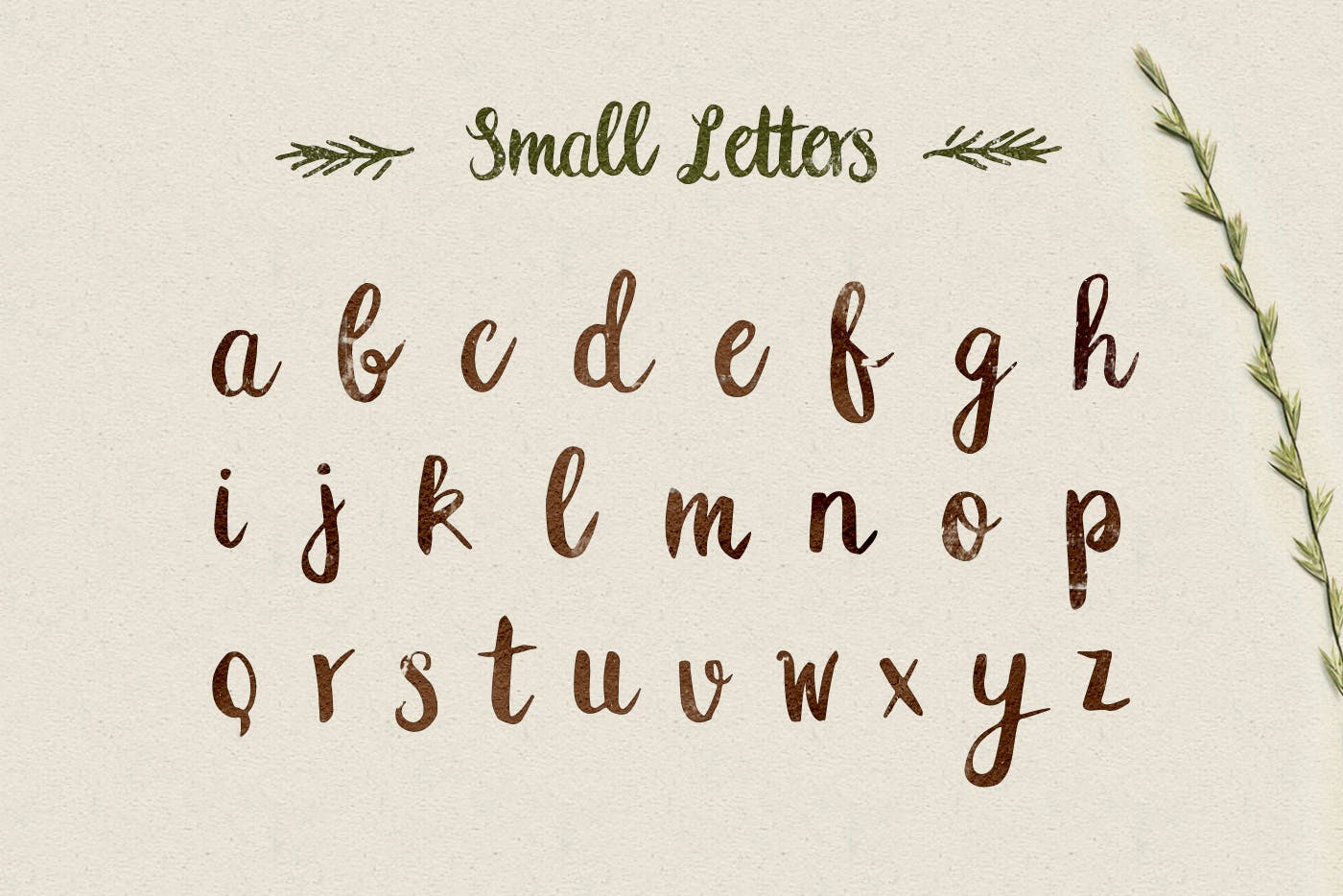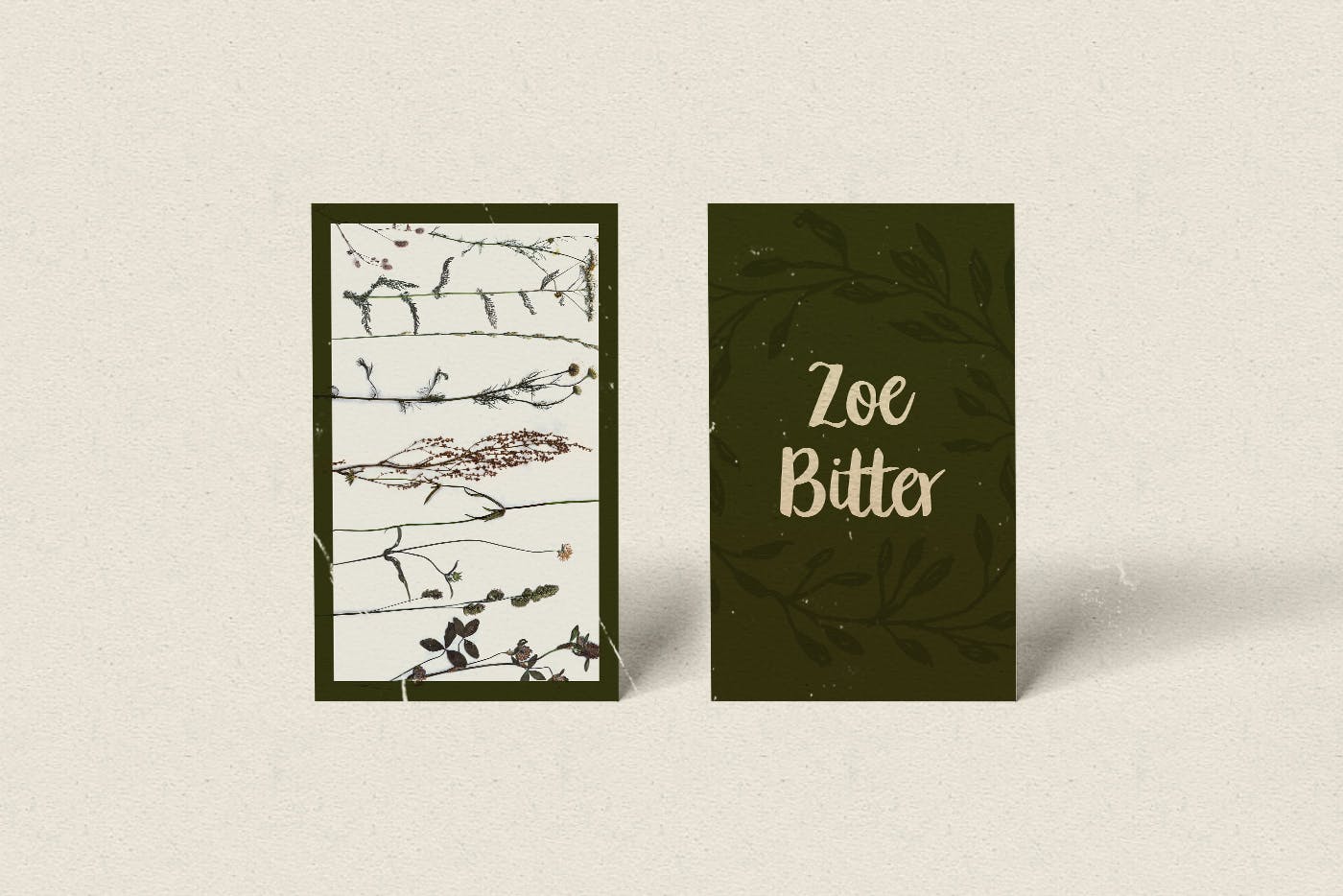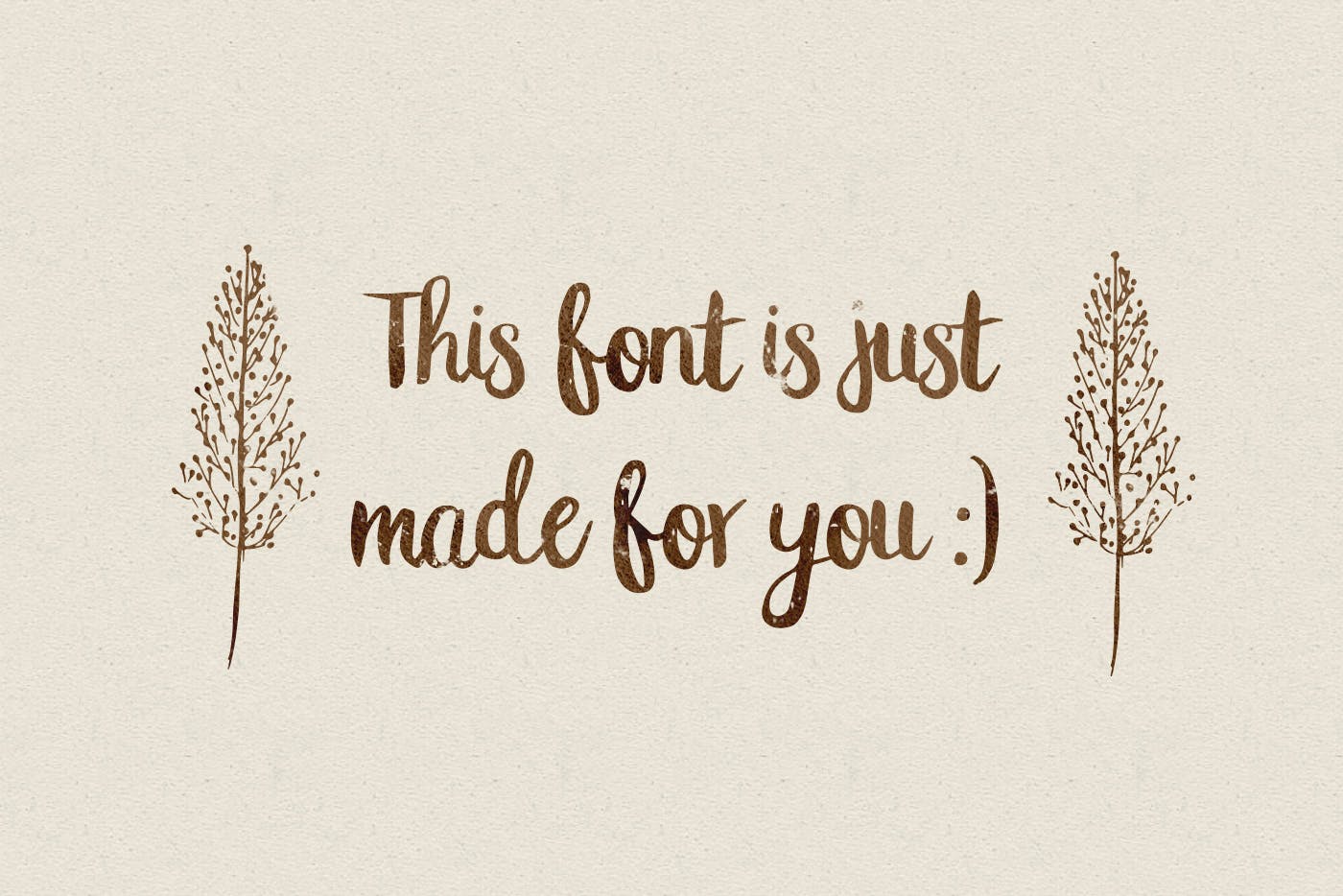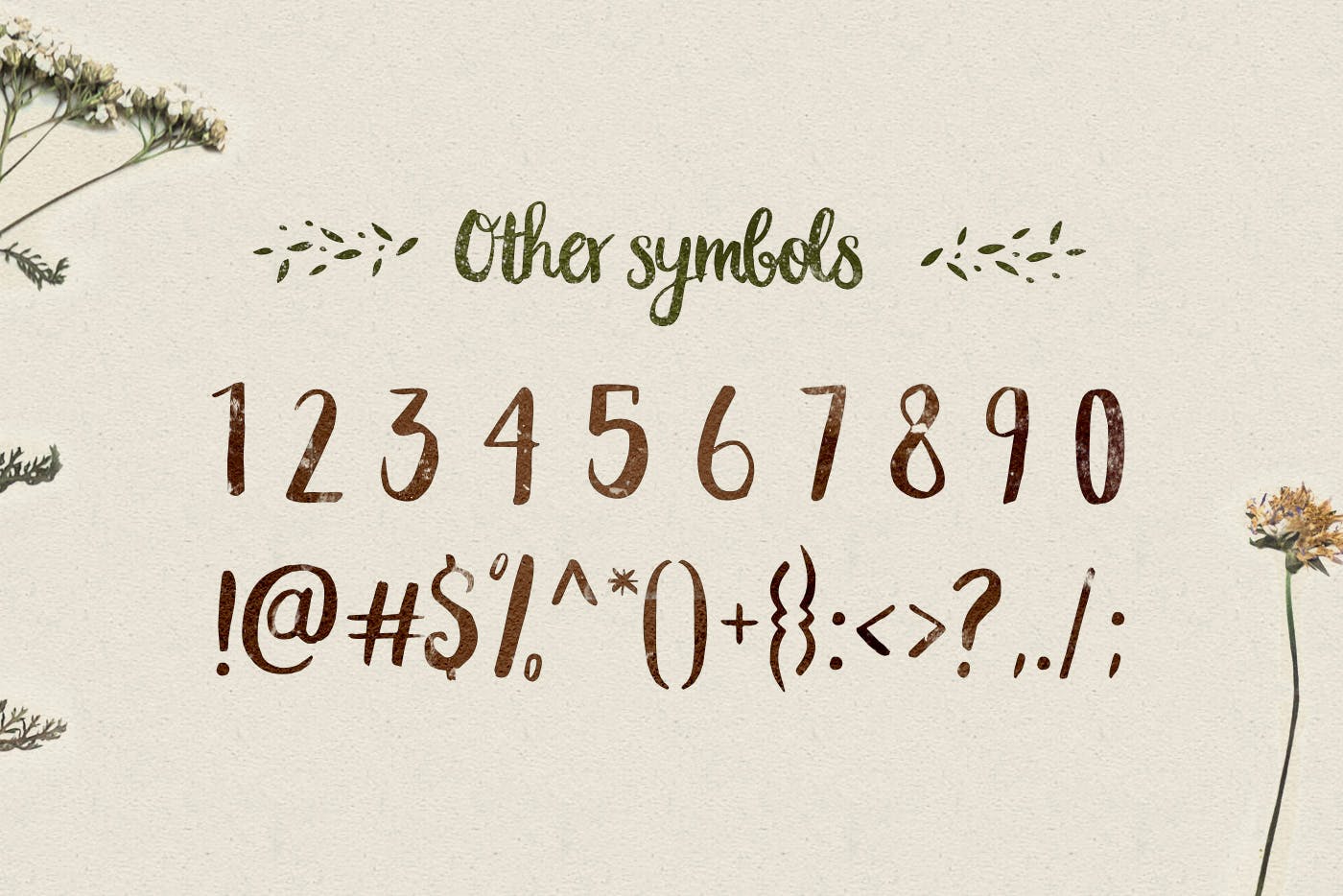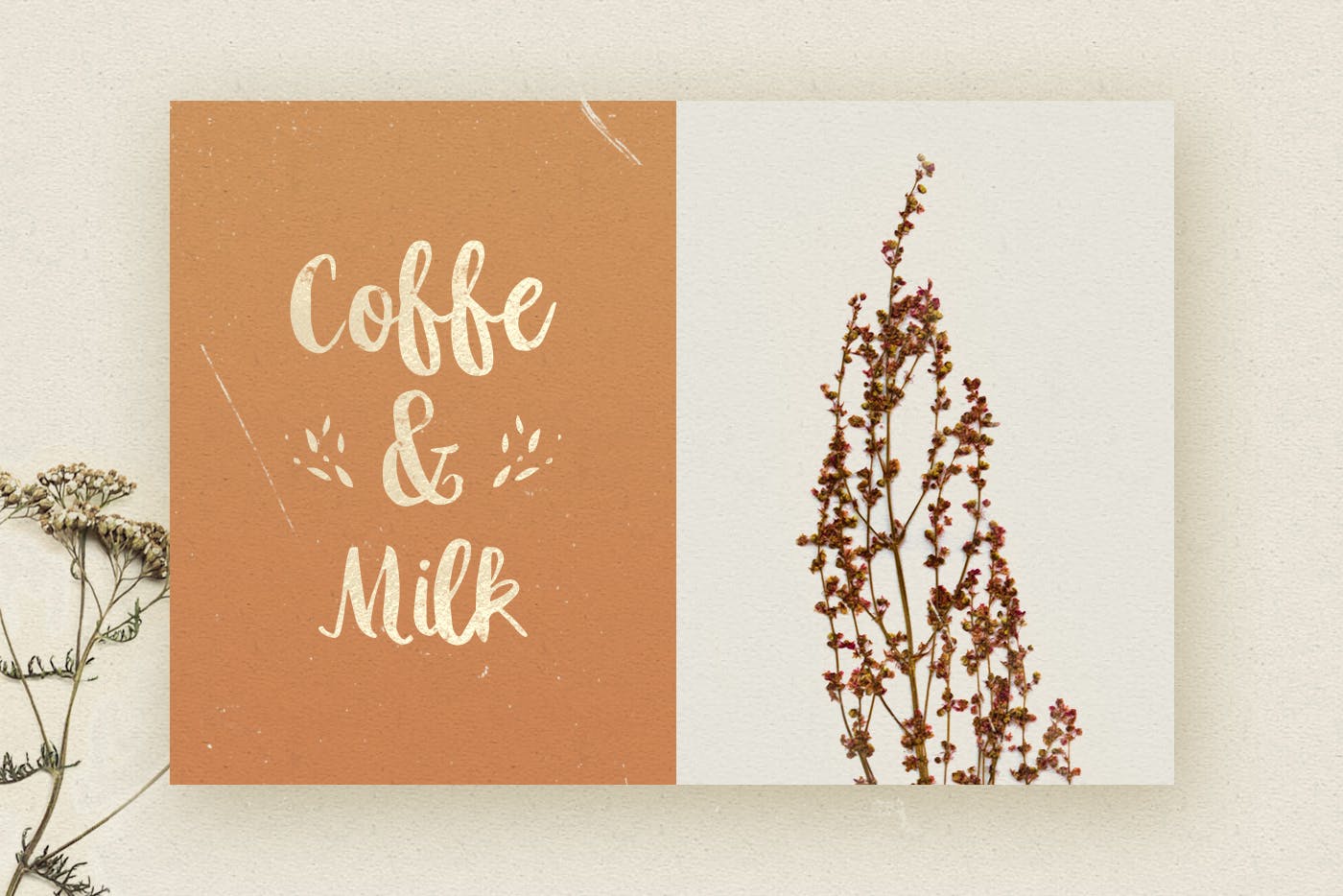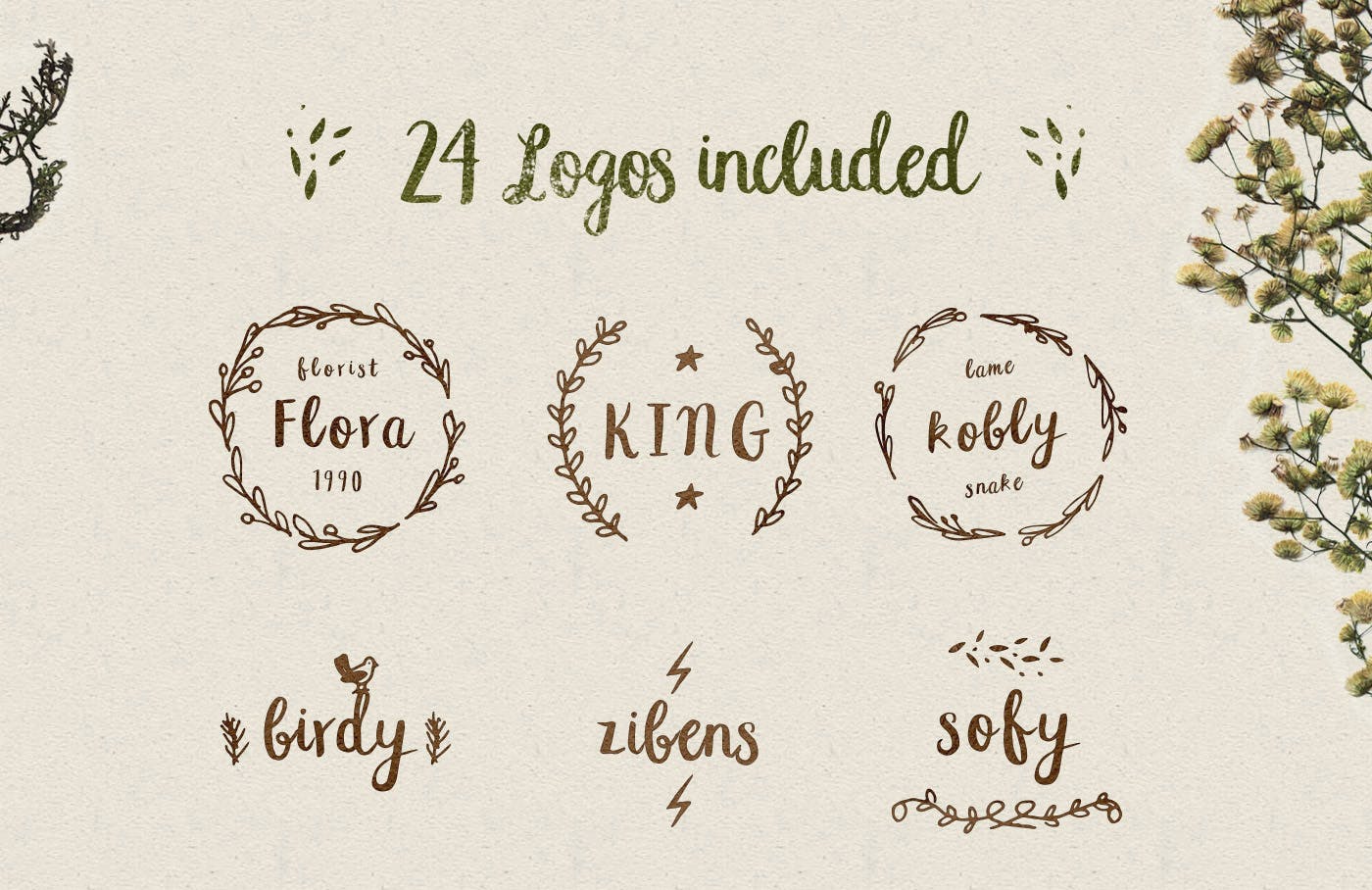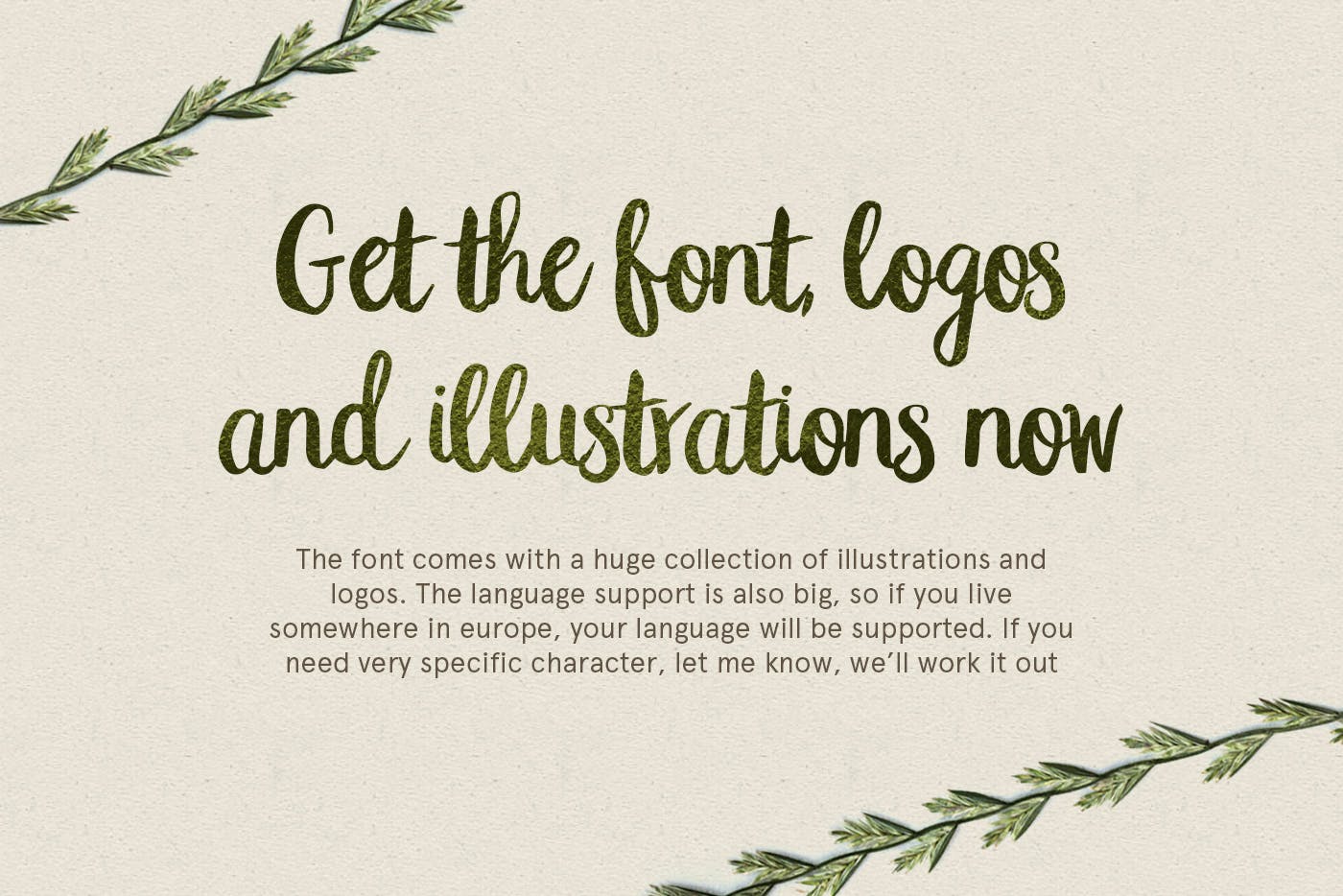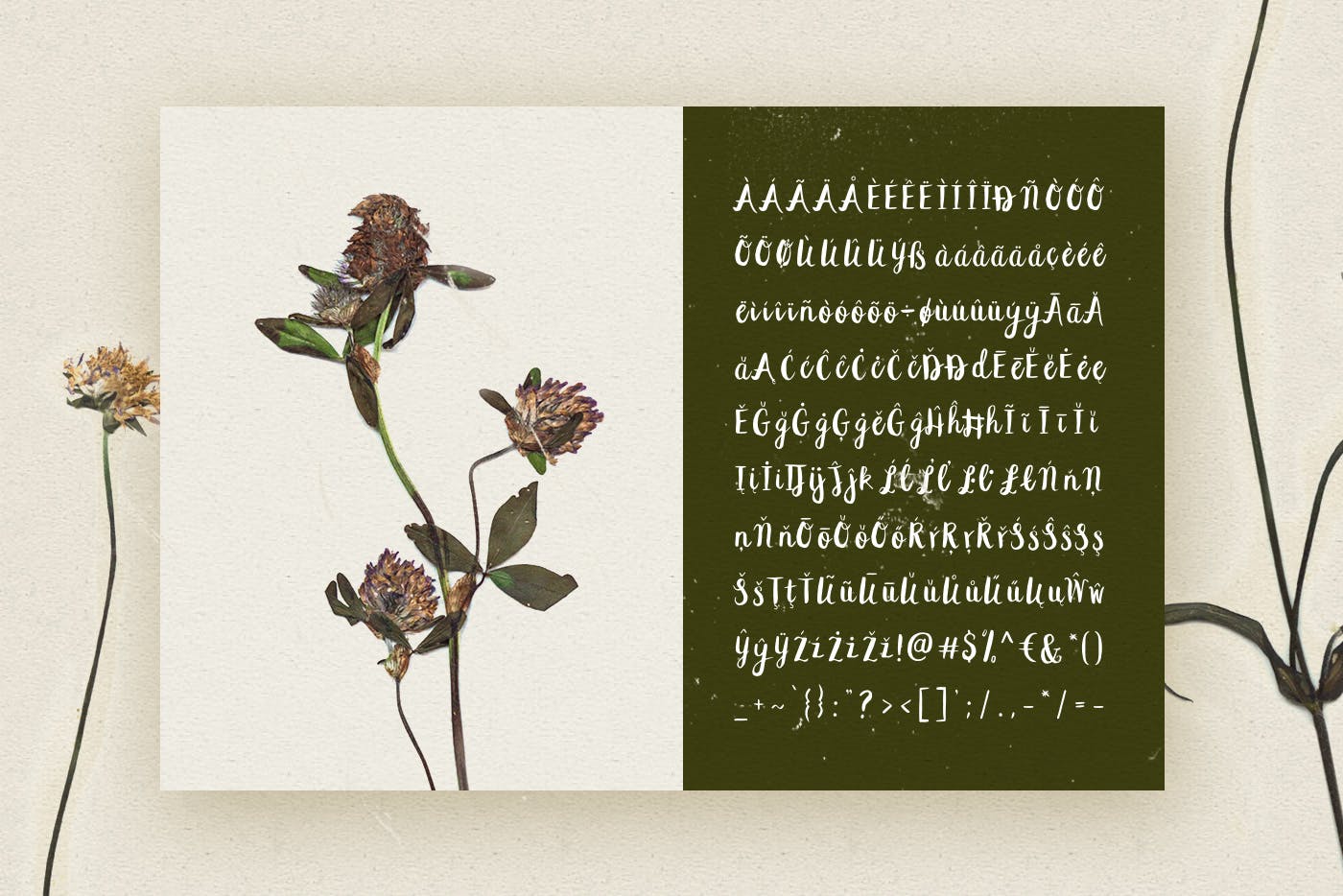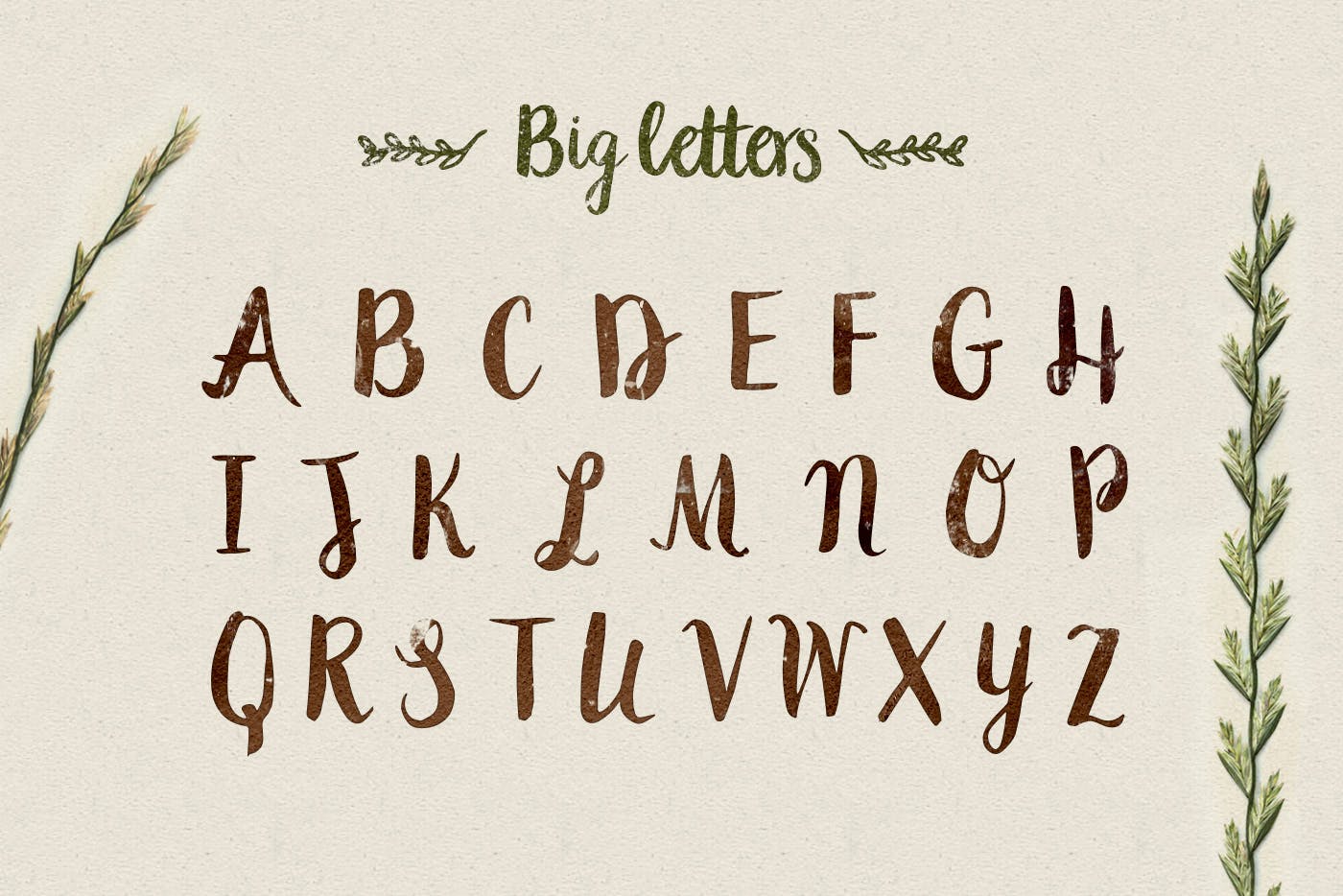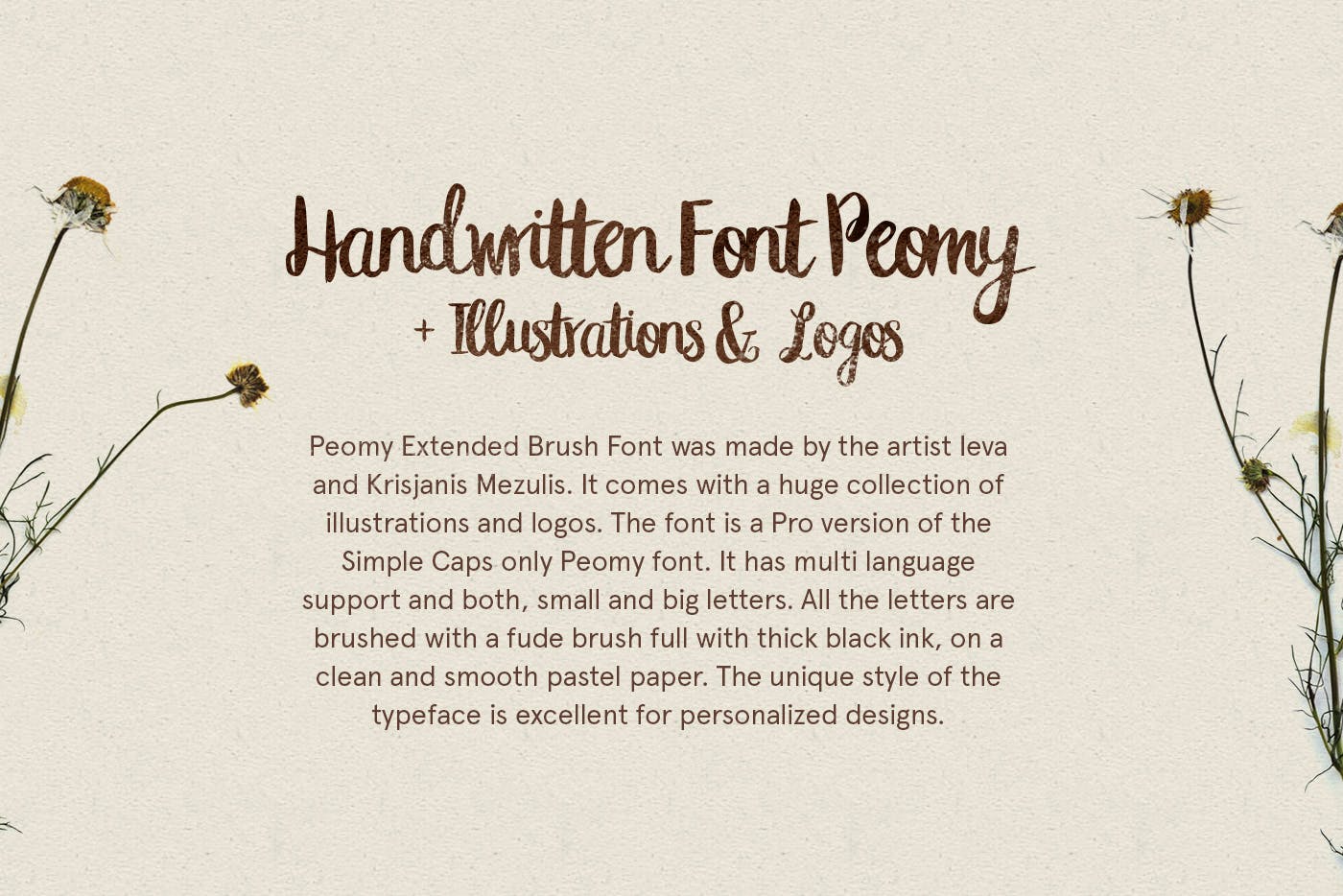
Peomy Extended Font + 150 Illustrations + 24 Logos
فونت Peomy توسط هنرمندانی به نامهای ایوا و کریسجیانیس مزولیس طراحی شده است. این فونت الهام گرفته از زیباییهای طبیعت و دشتهاست و از جمعآوری گلها برای یک هر بار شخصی الهام گرفته است. تمام حروف با قلم موی فوده و جوهر مشکی ضخیم بر روی کاغذ پاستل تمیز و صاف طراحی شدهاند.
این فونت شامل مجموعه عظیمی از دودیها الهام گرفته از طبیعت، وکتورهای طراحی شده و لوگوهای از پیش طراحی شده است. بهترین قسمت این است که همه چیز به راحتی قابل استفاده و ویرایش است :)
فونت دارای حروف بزرگ و کوچک است، بنابراین شما دامنه وسیعی از کاراکترها را برای استفاده در آثار تایپوگرافی دارید. این فونت ویژگیهای پیشرفته اوپنتایپ و کرنینگ پیشرفته را دارد و از پشتیبانی چند زبانه برخوردار است.
امکانات بیپایان برای خلاقان
بسته Peomy Extended شامل 24 الگوی لوگوی ویرایشپذیر است - بنابراین شما میتوانید در عرض چند دقیقه لوگوی بعدی خود را به راحتی ایجاد کنید. از آنها به همان صورت استفاده کنید یا آنها را تغییر داده و بهبود بخشید. همچنین شما 150 تصویر وکتوری دریافت میکنید که تمام نیازهای شما را پوشش میدهد، از برگها تا کیکها، از پرندگان تا چنگالها.